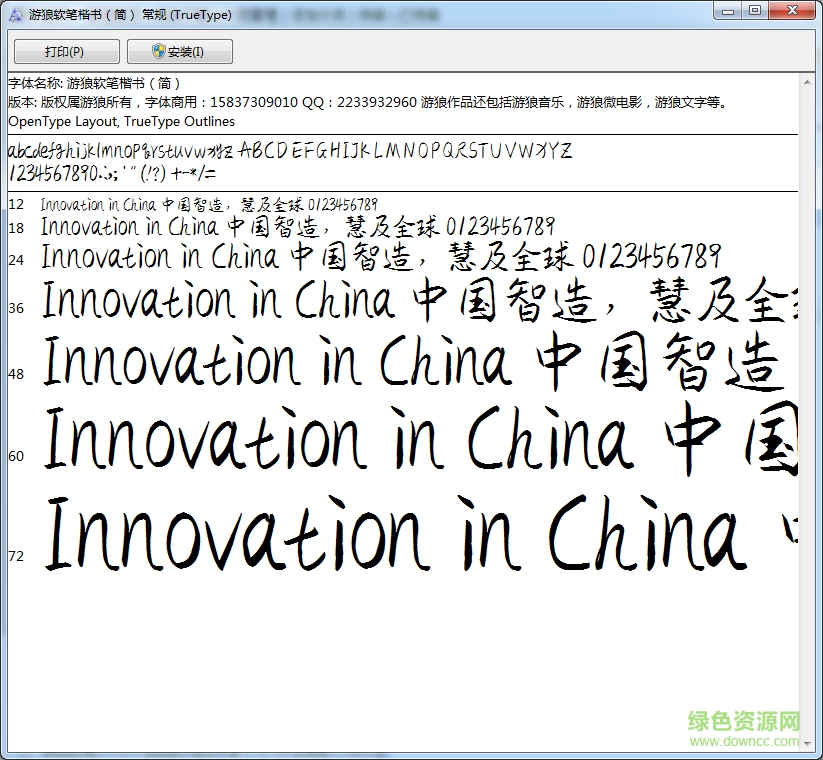
軟件介紹 軟件標簽: 游狼軟筆楷書 字體 游狼軟筆體是一款非常好用的楷書字體軟件,字體端正極具美感,使用流暢,滲透于多種行業(yè)領(lǐng)域??靵砭G色資源網(wǎng)下載體驗吧!游狼軟筆體介紹游狼軟筆體是一款極具個性的字體,該字體十分飄逸,彰顯了自己的個性。游狼軟筆楷書安裝方法一:控制面板/字體/文件/安裝新字體;方法二:直接將字體復(fù)制到C:\WINDOWS\Fonts。方法三:針對win7系統(tǒng),用戶只需選中字體右鍵安裝即可。 軟件截圖 上一張下一張(1 / 1) 安裝詳細截圖 猜你喜歡 楷書字體 楷書字體 楷書字體是綠色資源網(wǎng)小編專為大家收集的一類非常流行而且好用的楷書字體,它包括了各種形式的楷書。楷書也叫正楷、真書、正書。從程邈創(chuàng)立的隸書逐漸演變而來,更趨簡化,橫平豎直,筆勢雄奇,姿態(tài)橫生,可應(yīng)用于繪畫設(shè)計、藝術(shù)創(chuàng)作、平面廣告、印刷包裝、電視廣告等等各行各業(yè)。也是現(xiàn)在很多行業(yè)必用的一類字體,小編收集的這一類楷書字體希望能更好的幫助大家收集和使用楷書字體。 查看更多>> 楷體國標字體官方版 2.45M/中文/7.1/下載 漢儀閃耀楷書字體 1.77M/中文/0.0/下載 華為漢儀錦時楷書 2.92M/中文/5.0/下載 楷書字典手機版 4.46M/中文/5.0/v2.0 安卓版下載 經(jīng)典楷體繁體 3.96M/中文/5.0/下載 楷書繁體字體包 9.76M/中文/8.0/下載 其他版本下載 標題 大小 更新日期 下載 下載地址 電腦版 游狼軟筆楷書 點擊報錯 軟件無法下載或下載后無法使用,請點擊報錯,謝謝! 關(guān)閉報錯反饋 請描述您所遇到的錯誤,我們將盡快予以修正,謝謝! *必填項,請輸入內(nèi)容 本類最新 dreamweaver字體庫 首爾南山體字體 v1.06 官方版 潮字社風云簡ttf 潮字社凌渡鯤鵬簡體字體 潮字社曾玉波手書簡字體 微博慧心字體 相關(guān)文章 Photoshop字體安裝使用方法和技巧 如何解決“無法新增字體”問題 Win 7系統(tǒng)安裝字體方法 網(wǎng)頁字體大小設(shè)置方法 怎么改網(wǎng)頁字體大小 在Linux系統(tǒng)中安裝字體的幾種方法 windows7字體顯示問題:打開某些程序的時候顯示的是亂碼 用戶評論 熱門評論 最新評論 發(fā)表評論 查看所有評論(0) 昵稱: 請不要評論無意義或臟話,我們所有評論會有人工審核. 字數(shù): 0/500 (您的評論需要經(jīng)過審核才能顯示)